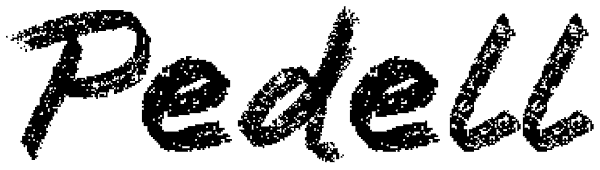
Pedell
Pedell ist eine neue Schreibschrift, die das Schreiben mit Kreide simuliert. Ein Font mit eben diesem ‚Kreidecharakter’ fehlte bisher noch in der profonts Library. Also wurde der Schriftdesigner Ralph M. Unger beauftragt, eine Kreideschrift zu...